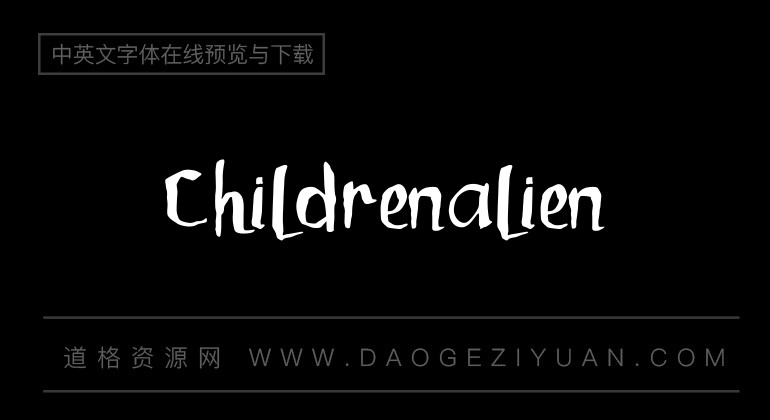
Childrenalien 是一款由英国设计师Richard Miller设计的字体,它是一种易于阅读的、具有艺术感的字体,它特别适合用于儿童和青少年的项目,如游戏、电影、教育等等。Childrenalien字体具有清晰的结构,粗细的线条,以及可爱的外观,可以帮助设计师创造出充满活力和有趣的作品。内容介绍
Childrenalien是一款非常不错的手写艺术字体,具有很好的视觉感,适合于文化类的宣传设计、商业类品牌的广告和产品包装设计以及个性化文字排版等较多场景。